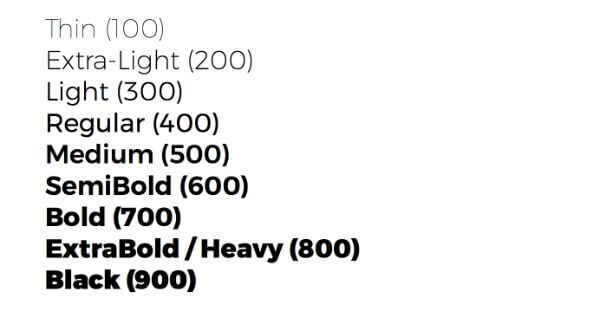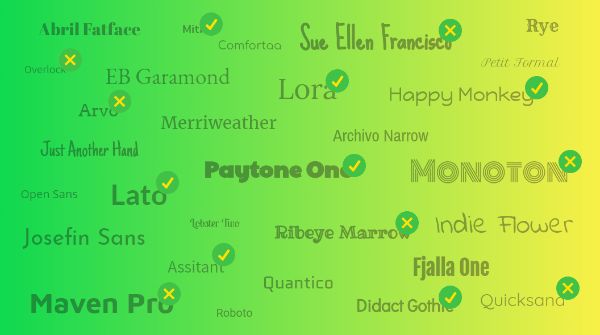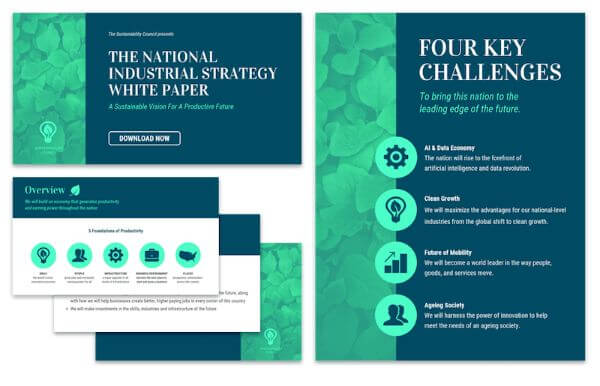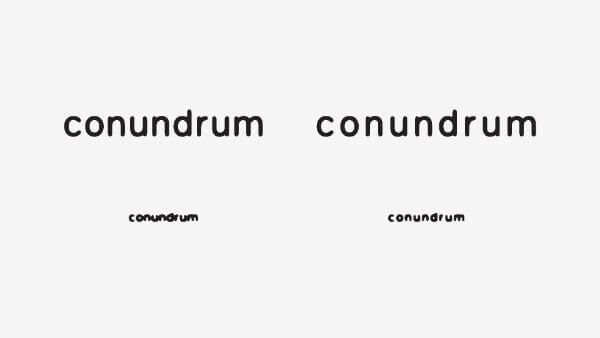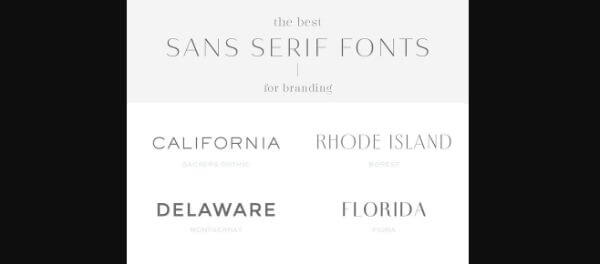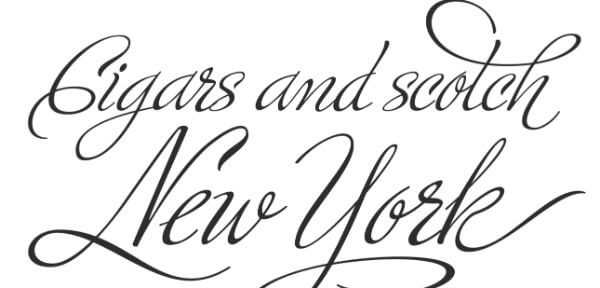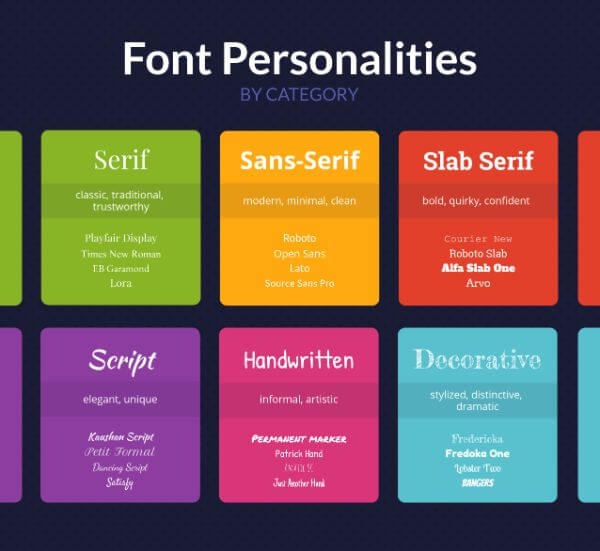
知っておきたい!ブランドのイメージを左右するロゴの書体デザインのための5つのヒント
どのブランドにも、人々が認識できる独自のアイデンティティが必要です。そして、ブランドのアイデンティティを構築するのは簡単なことではありません。ロゴのデザイン、名刺のデザイン、ブランドを表す色やフォントなど、独自のブランドアイデンティティを十分に理解する必要があります。工程はこれだけではありません。デザインが準備できたら、それが自社やターゲットに響くかどうかを確認しなければなりません。
このブログでは、ブランドに適した書体をデザインするためのヒントについて説明します。選択するべきフォントは、明確で、覚えやすく、読みやすく、プラットフォームに依存しないものでなければなりません。さらに、それはブランドの個性を伝えるものでなければなりません。
1. ブランドの個性を理解する
それぞれのブランドは、その個性や特徴によって認識されています。顧客は、明確でつながりやすいブランドの個性を覚えています。こういった要素を見ることで、ブランドを理解し、認知度を高めることができます。ブランドの声、色の組み合わせ、ロゴ、フォントは、ブランドの個性と連動している必要があります。
また、ブランドの個性は、ターゲットのユーザーに適切なメッセージを伝えるようなものでなければなりません。したがって、フォントを探す前に、ブランドの個性について考え、それがよく定義されているかどうかを確認してください。そうでない場合は、あなたのブランドを人々にどのように認識してもらいたいかを確認し、理解してください。
どのようにして実際のブランドの個性を理解し、投影すればいいのかわからない場合は、ブランドの個性と一致する形容詞をいくつか探してみてください。例えば、ステークホルダーを巻き込んで、いくつかの用語をピックアップしてもらうことができます。
これらの用語は、ブランドの個性を部分的に、あるいは全体的に定義する言葉にすることができます。大胆、冷静、柔軟、友好的、機能的、真面目、信頼できる、風変わり、洗練された、暖かい、などの用語を提供することができます。
このような言葉は、あなたのブランドの個性に関する理解を定義するのに役立ちます。個性が完璧に定義されたら、その根底にあるメッセージを正当化するフォントを探すことができます。
2. すべてのフォントの個性をキュレートする
タイポグラフィの概念にあまり精通していない場合は、もしかしたらフォントのカテゴリについて何も理解していないかもしれません。しかし、フォントのカテゴリを理解することは、ブランドに適したフォントを見つけるための調査を開始する優れたポイントです。
フォントのカテゴリは、フォントを識別、選択、およびペアリングしようとするグラフィックデザイナーを支援する書体の分類として定義されています。すべてのグループには特定の独自の特徴があり、これを理解すると、ビジネスに適したフォントを見つけるのに役立ちます。これらのフォントカテゴリについて十分な知識があれば、さまざまなフォント間の選択肢を候補から絞り込めるので、時間を大幅に節約できます。
フォントは6種類に分類できます。
・セリフ
・スラブセリフ
・サンセリフ
・手書き
・スクリプト
・装飾的
1. セリフ体
最も古いフォントであるセリフ体は、15世紀頃から存在しています。名前の由来は、各文字の頭と足元にある小さな飾りに由来しています。元々の性質から、セリフ体は一般的に上品で伝統的なものとして見られ、信頼に値するものとされています。
尊敬を集めながらも伝統的な外観を求めるブランドは、このフォントをブランドに採用することが多いです。例えば、Time、Vogue、Tiffany & Co.などのブランドは、ブランドやブランドの個性を表現するためにこれらのフォントを使用しています。
セリフ体のカテゴリに該当する人気のフォントには、Times New Roman、EB Garamond、Playfair Display、Baskervilleなどがあります。
2. サンセリフ体
サンセリフ体は、そのデザインと形において、現代的でクリーンでミニマルなものと理解されています。19世紀頃まで登場しなかったため、セリフ体に比べて現代的で新しいと考えられています。シンプルでクリーンな外観を持つサンセリフは、多くの場合、素直で分かりやすいものとして見られています。
サンセリフ体は、その大胆なフォームで、最近のWeb上では非常に多くの企業に採用されています。Facebook、Google、Netflix、Spotifyなどのテクノロジー企業は、ロゴデザインにこれらのフォントを使用しています。
標準のサンセリフ体にはHelvetica、Arial、Roboto、Source Sans Proなどがあります。
3. スラブセリフ体
ブランドを大胆に、風変わりに、そして自信に満ちたものにしたいのであれば、スラブセリフ体を選ぶべきです。このフォントは、その風変わりなフォルムと精神で知られています。その結果、従来のセリフ体よりも無骨で大胆に見えます。
ブランドに伝統的なアプローチと現代的なアプローチを融合させたい場合は、このフォントが最適です。企業の存在が長い歴史を持ちながらも、現代的でもありたい場合は、このフォントを採用しています。例としては、Volvo、Sony、Hondaなどがあります。
スラブセリフ体のカテゴリに該当するフォントは、Rockwell、Roboto Slab、Courier Newです。
4. スクリプト体
スクリプト体は優雅さを表しており、一つの文字が後続の一文字につながっている筆記体の筆跡を再現したデザインになっています。誰もが個性的な筆跡を持っていることはおわかりでしょう。
同様に、このカテゴリに属するフォントは、どれも個性的な外観です。スクリプト体は、トレンドに乗りたいときに使用されますが、トレンドが終わるとブランドのフォントがパターンから脱落してしまうリスクも抱えています。一部のブランドでは、長く使われ続けてきたこれらのフォントを使用しています。
例えば、Johnson&JohnsonやInstagram、Fordなどのブランドは、このフォントを選んでいるにもかかわらず、遠くからでもブランドを識別することができます。このカテゴリに該当する人気のフォントは、Lucida Script、Pacifico、Allura、Dancing Scriptなどです。
5. 手書きフォント
読んで字のごとく、手書き風のフォントです。このカテゴリのフォントは、まるで人の手で書かれたように見えます。このフォントは、ある意味でとんでもない文字の形やストロークを持っており、従来のセリフ書体と比較すると大きく異なります。
ブランドがアートに関連している場合や、親しみやすく温かみのあるものとして出会う必要がある場合、これらのフォントは最適です。
手書きフォントに該当するフォントには、Knewave、Permanent marker、Patrick Handなどがあります。
6. 装飾的なフォント
最も多様なフォントのカテゴリは、装飾的なフォントです。これには、ブランドロゴの外観を定型化するさまざまなストローク、形、および形状を持つフォントが含まれます。Disney、IBM、Legoのようなブランドは、記憶に残りやすく、認識しやすいように、このフォントを採用しています。
強力なフォントなので、最小限に使用する必要があります。トレンディに見えるため、企業ブランドを今後数年にわたって維持したいのであれば、避けた方が良いでしょう。このカテゴリに該当するフォントは、Fredericka、Lobster Twoなどです。
したがって、すべてを要約すると、フォントのカテゴリはブランドに次のようなメッセージを与えます。
セリフ:クラシックで伝統的
サンセリフ: モダン、プロフェッショナル、ミニマル
スラブセリフ:風変わりでありながら、大胆で自信に満ちている
スクリプト: エレガントではっきりしている
手書き:気楽でありながら芸術的
装飾的:ドラマチックでスタイリッシュ
3. フォント用の予算をキュレートし、そのライセンス要件を理解する
さて、フォントのカテゴリとそれに該当するフォントを理解したところで、今度は自分のブランドのためのフォントを選ぶ作業に移ることができます。しかし、その前に、どこからフォントを取り入れることができるのかを調べなければなりません。探しているフォントスタイルが無料で利用できるかどうかを確認する必要があります。
そうでない場合は、予算内でどのフォントが利用できるか、ニーズに合っているかどうかを判断する必要があります。Googleフォント、Font Squirrel、Fontライブラリといった特定のフォントライブラリは、無料で利用できるフォントを提供しています。無料のフォントは、多くの場合、便利であり、採用するには正しい選択です。
しかし、フォントライブラリは、無料用に選ばれたフォントのみを提供します。そのため、太字や斜体などのインスタンスはほとんどありません。さまざまな太さやスタイルを持つフォントファミリーを見つけるのは困難です。有料ライセンスを提供しているフォントライブラリには、Adobeフォント、Linotype、Fonts.comなどがあります。
フォントライブラリは膨大なオプションを提供していますが、費用もかさむでしょう。さらに、これらのライブラリは、フォントライセンスごとに個別に料金を請求します。Webアプリ用、モバイルアプリ用、印刷メディア用のフォントを探しているのであれば、3つすべての費用を負担しなければなりません。有料フォントか、無料フォントか、選択肢はありますが、それがブランドの個性と根本的なメッセージと一致するようにしてください。
4. ブランドのペルソナに一致するフォントスタイルを選択する
ブランドのペルソナとフォントの様々なカテゴリに慣れてきたら、ブランドのフォントの選択を試してみるべきです。しかし、フォントの文字が関係している場合、フォントのカテゴリだけでは全体のストーリーを知ることはできません。
ブランドに使用する際にフォントの雰囲気に影響を与えるフォントスタイルごとに、多くのバリエーションがあります。したがって、フォントをどのように組み合わせるかは、ブランドの理解とメッセージを伝える上で重要な役割を果たします。
ブランドの個性の変化に応じて、どのようにフォントを組み合わせるべきかを見てみましょう。大胆なセリフ体のタイトルと、控えめなサンセリフ体の組み合わせは、親しみやすく信頼できるアイデアを提供します。セリフとサンセリフの違いが自然にペアを形成し、サンセリフの現代的な特徴とセリフの錆びつき感とのバランスを取ることができます。
2. ブランドのフォントが、様々なフォントの太さで利用可能であること
テキストの階層を構築するには、ブランドスタイルのガイドに記載されるべき、ライト、レギュラー、セミボールド、ボールドのような様々なフォントの太さが必要です。様々なヘッダーとサブヘッダーを切り替えるにも、様々なフォントの太さが必要です。
3.ブランドのフォントの読みやすさ
様式化された形や規則とは無関係に、見分けやすく理解しやすいフォントが、ブランド固有のフォントとしての資格を持つべきです。様式化された形には、太字、斜体、大文字、小文字のフォント、様々な太さのフォントなどがあります。ヘッダーやサブヘッダーに関しては、読みやすさは必要ありません。しかし、コンテンツの本文部分のテキストには読みやすいフォントが必要です。
結論
適切なフォントサイズとスタイルを選ぶことは、デザイナーにかなりの課題を与えます。フォントを確定する前に慎重かつ徹底的に考えなければなりません。これまで述べてきたヒントは、ブランドのペルソナに応じてブランドに適したフォントを選択する方法についての洞察を提供しています。